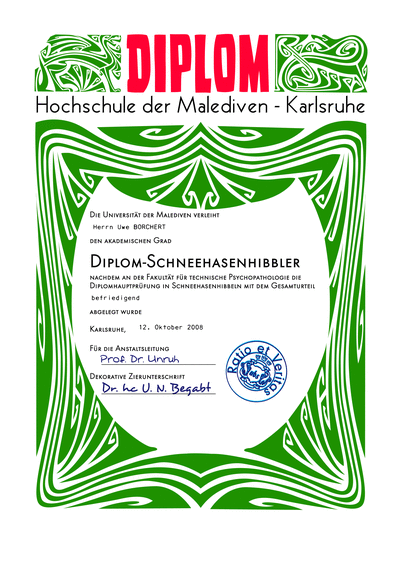
schöne Urkunden (Sport)
Ich hab die - für mich schwierige - Aufgabe, eine Urkunde im Bereich Breitensport zu gestalten, nach dem Schema "Teilnehmer X hat an Veranstaltung Y erfolgreich teilgenommen, und hat den würdevollen Platz Z erreicht. Die Unterzeichnenden", und tu mir dabei unheimlich schwer ...
Hat jemand vielleicht eine Sammlung, wie man sowas *gut* aussehen lassen könnte?
Alles was ich hinkriege ist bisher mehr als lausig. :?
Haha, das hab ich einmal machen müssen. War aber ein zwei-Stunden-Job für ne Spaßveranstaltung von einem Verein, in dem ich selbst auch Mitglied war. Ich trau mich nicht, das Ergebnis hier zu posten :roll:
… wie sowas *gut* aussehen soll, ist eine gute Frage. Kommt halt auch sehr drauf an, ob es wirklich wie eine klassische/ernsthafte/feierliche «Urkunde» wirken soll oder Du es doch irgendwie neu/«frisch» interpretieren kannst?
:) schön dass es nicht nur mir so geht ...
Ja, das Ding soll eingerahmt an der Wand hängen.
Grundsätzlich ist die ganze Veranstaltung definitiv nicht "angestaubt" oder sowas ... das Erscheinungsbild an sich ist durchaus zu verkraften. Aber die Urkunde als solche will partout nicht reingehen ...
Flickr ist auch keine Hilfe :(
dann nimm die ci-schrift, lass das ganze klassisch-fad im mittelachsensatz herunterlaufen (eine der wenigen anwendungen, wo das zentrieren fast pflicht ist), bissl mit größen gewichten und damit es was gleichschaut, such dir (oder wenn du zeit hast: mach selber) einen netten ev. zum veranstalter oder zur sportart passenen hintergrund, der vielleicht wasserzeichenähnlich leicht und abgesoftet drunter steht.
nüchterne typo und der hintergrund für die stimmung und paaasst.
fraktur
Auja geil: nimm eine moderne Gebrochene, die keiner lesen kann :hammer: Sangue oder Kaas oder so. Oder Fakir?
Und wenn’s das Budget hergibt, mach 'ne schöne Blindprägung drauf. Oder noch viel besser (aber teurer) Reliefprägung!
Kennt jemand eine Webseite, auf der man gelungene Urkundengestaltungen finden kann? Die meisten Urkunden sind ja nach Schema F aufgebaut – da muss es doch auch bessere Beispiele geben? :P
Ein empfehlenswertes Buch zu diesem Thema:
Stähle – Linz – Kurz
DIE URKUNDE
Entwurf – Schrift – Typographie – Einbandgestaltung
Karl Gröner Verlag, Ulm-Donau
Besten Dank für die Buchempfehlung. Ich konnte es für wenige Euro im Antiquariat erstehen. Für den Preis wirklich ein Schnäppchen, da man sich wunderbar in die Gestaltung von Urkunden und Veredelungstechniken einlesen kann.
Leider scheint es, als wäre das Buch zum Zeitpunkt der Veröffentlichung bereits schon etwas veraltet gewesen. Die Beispiele sind mir in der Großzahl dann doch etwas zu klassisch-traditionell geprägt. Sachliche Entwürfe sieht man kaum – Urkundenentwürfe mit Grotesk-Schriften sind ebenfalls Mangelware.
Die Urkundengestaltung scheint wirklich kein besonders beliebtes Thema zu sein. Bei meinen Recherchen bin ich auf maximal mittelmäßige Entwürfe gestoßen. Selbst Urkunden aus Hochschulen, denen ein Design-Fachbereich angehört, sind oftmals mehr schlecht als recht gestaltet.
Das beste Beispiel einer zeitgemäßen Gestaltung fand ich hier.
Das kann doch nicht alles sein?
Willkommen im Club! Ich habe vor 3 oder 4 Jahren die gleiche Erfahrung gemacht. Auch meine Art Direktrize konnte mir nicht weiterhelfen. Dabei kam dann auch nur etwas irres raus.
Danach habe ich verzweifelt aufgegeben. Hier im Faden habe ich leider auch nicht sehr viel Anregung finden können.